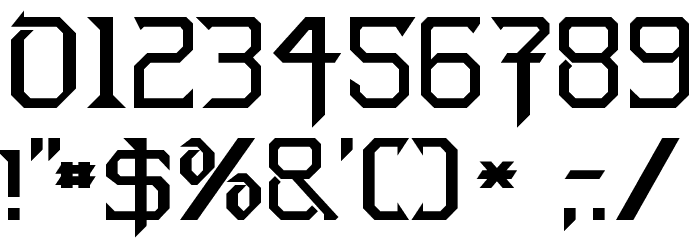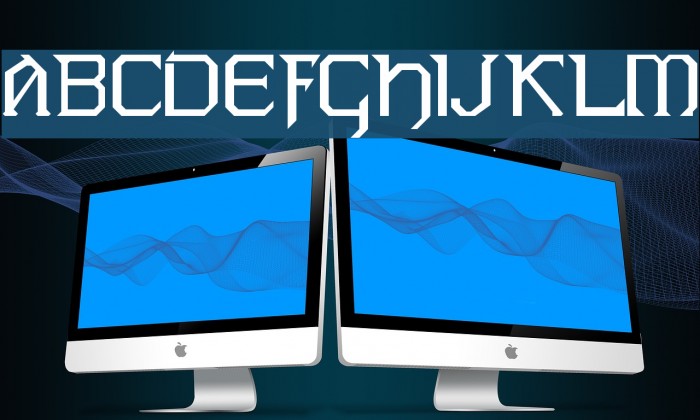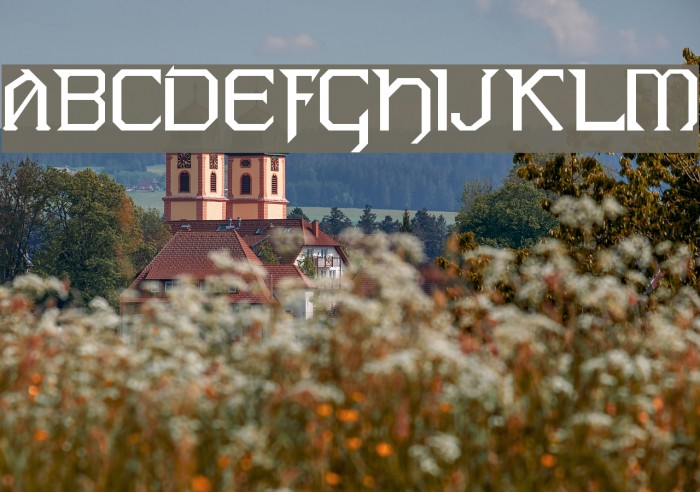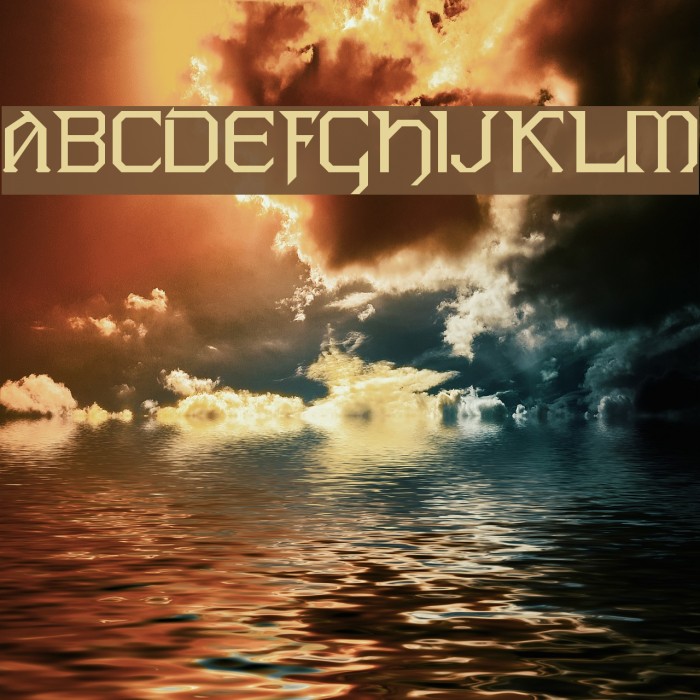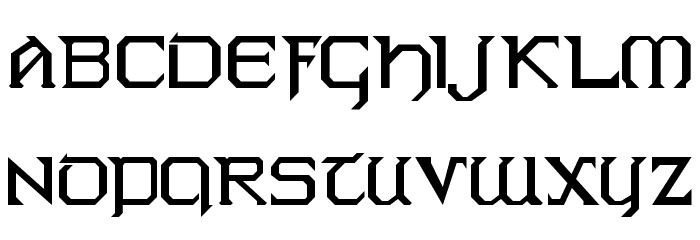
Warlords Normal Font
✎ Gothic
| श्रेणियाँ | Gothic |
| कंट्रास्ट | High |
| उपयोग का मामला | Headlines, Logos |
| सुझाए गए प्रोजेक्ट | Ideal for video game titles, movie posters, branding for edgy products, and any project requiring a strong, impactful visual presence. |